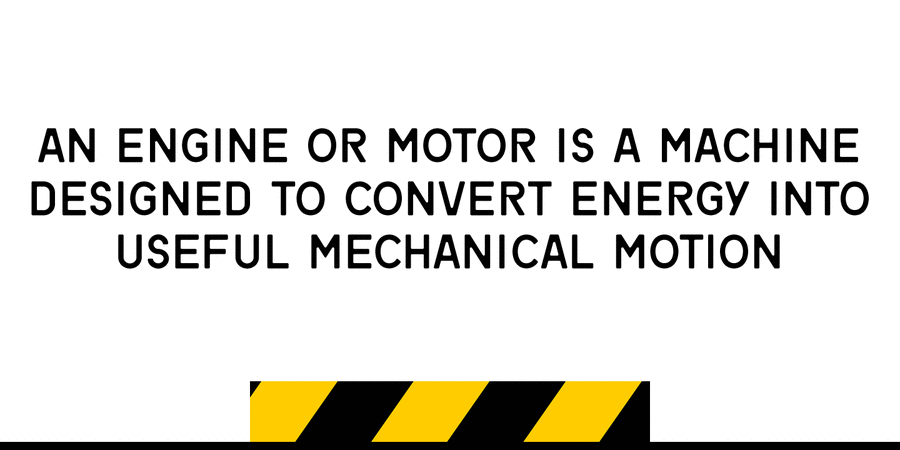
Мотор — акцидентный щрифт, сделан по мотивам букв автомобильных номерных знаков, принятых в России. Разработан Сергеем Ткаченко в 2014 году.
Асоціації з сімейством шрифтів Motor 4FОсобистість і характер гарнітури:
точний, рівний, переконливий, прямокутний, стабільний, статичний, Простий, нейтральний, прямий, сучасний, глобалізований, глобалістічний, монотонний, логічний, прагматичний, практичний, твердий, лаконічний, доступний, серйозний, залізний, сталевий, надійний, впевнений, сильний, стійкий, автоматичний, штучний, холодний, машинний, інженерний, індустріальний, техногенний, військовий, армійський, стандартний, міський, грубий, робочий, байдужий, мотивуючий, залізничний, важливий, важкий, суворий
промисловість, техніка, верстат, код, тара, електростанція, енергетика, армія, зброя, машинобудування, завод, креслення, конструктор, інженер, автоматика, автомобіль, мотор, ГОСТ, прес, Місто, навігація, наука, шахта, шахтар, шолом, уніформа, вагон, авіація, літак, страйкбол, будівництво, технології, залізниця, паливо, робочий, ремонт, шоу, телебачення, вантажівка, позашляховик, взуття, цегла, далекобійник, сталевар, двигун, Доставка, нафта Гарнітура має ознаки стилів: